Madonna aposta em tipografia viral para falar com a geração TikTok
A agência por trás do álbum "brat", de Charli XCX, criou a tipografia do próximo disco de Madonna, "Confessions on a Dance Floor II"
Madonna anunciou seu novo álbum, "Confessions on a Dance Floor II" com uma tipografia sem serifa criada pela mesma agência responsável por "brat", de Charli XCX.
Em pôsteres colados nas ruas e vídeos curtos publicados nas redes sociais, Madonna deu pistas sobre o novo disco (que chega em 3 de julho) e sobre o primeiro single, “I Feel So Free”, usando apenas texto.
“Madonna Confessions II” aparece na capa em Helvetica, uma fonte sem serifa clássica e extremamente popular, conhecida por seu visual minimalista, simples e atemporal.
A tipografia domina toda a comunicação do lançamento: expressões como “Confessions II”, “COADF 2” e outros textos promocionais surgem em caixa alta, com fontes sem serifa. Em alguns casos, as letras aparecem esticadas verticalmente ou apenas contornadas.
A cantora não aposta em uma única fonte, mas em um verdadeiro repertório tipográfico. Em um vídeo nos Stories do Instagram, palavras piscam e se repetem verticalmente na tela, acompanhadas de um aviso de luz estroboscópica. O resultado é intenso, rápido e impossível de ignorar.
Um novo logotipo provocativo, com a letra “M”, mostra as pernas da cantora em botas prateadas de salto alto formando a letra por trás de uma caixa de som.
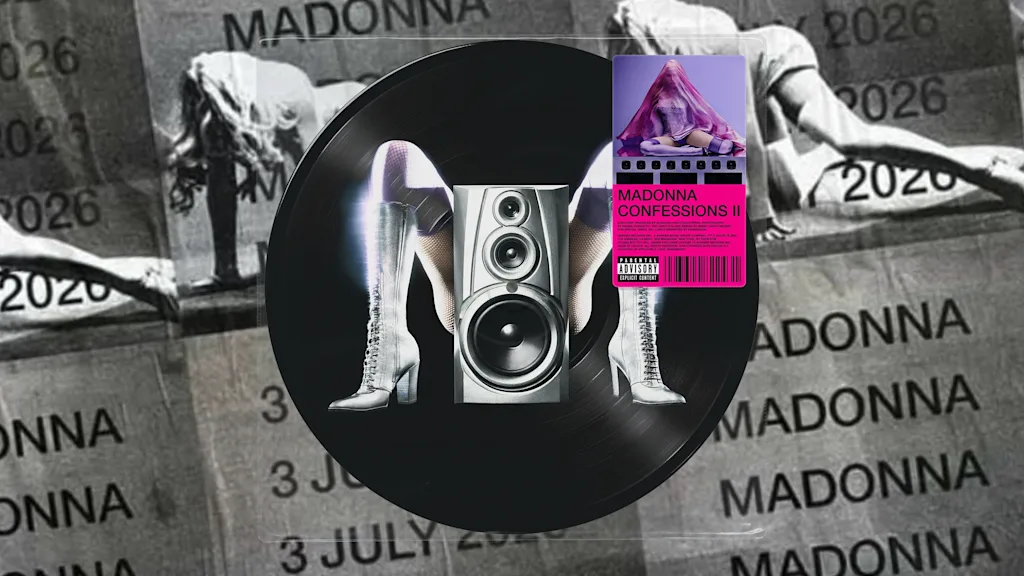
Para a sequência de seu icônico álbum de pop dance de 2005, Madonna voltou a trabalhar com o produtor Stuart Price, responsável por gravar, coproduzir e coescrever o disco original.
O trecho divulgado da primeira faixa reforça essa conexão, mergulhando diretamente no universo pop dance que marcou o álbum original. Já no design gráfico, Madonna optou por uma nova parceria criativa, desta vez com uma abordagem centrada na tipografia.
A agência Special Offer, Inc. já trabalhou com artistas como Haim e Miley Cyrus, mas ganhou destaque global com a direção de arte de "brat", lançado em 2024.
O álbum de Charli XCX, conhecido pela paleta verde neon e pelo uso da fonte Arial Narrow desfocada, levou o prêmio de Melhor Pacote de Gravação no Grammy de 2025.
Depois do lançamento, a estética do texto de "brat" se espalhou rapidamente: virou mural, gerador não oficial de capas, estampou produtos licenciados (e não licenciados) e apareceu até em versões de luxo do álbum.
Se antes Madonna promovia sua música em plataformas como a MTV, hoje é o vídeo curto que dita o ritmo da atenção. A estratégia visual baseada em tipografia adotada pela Special Offer, Inc. funciona perfeitamente em telas de smartphone, onde textos curtos, fortes e visualmente impactantes fazem o usuário parar de rolar o feed.
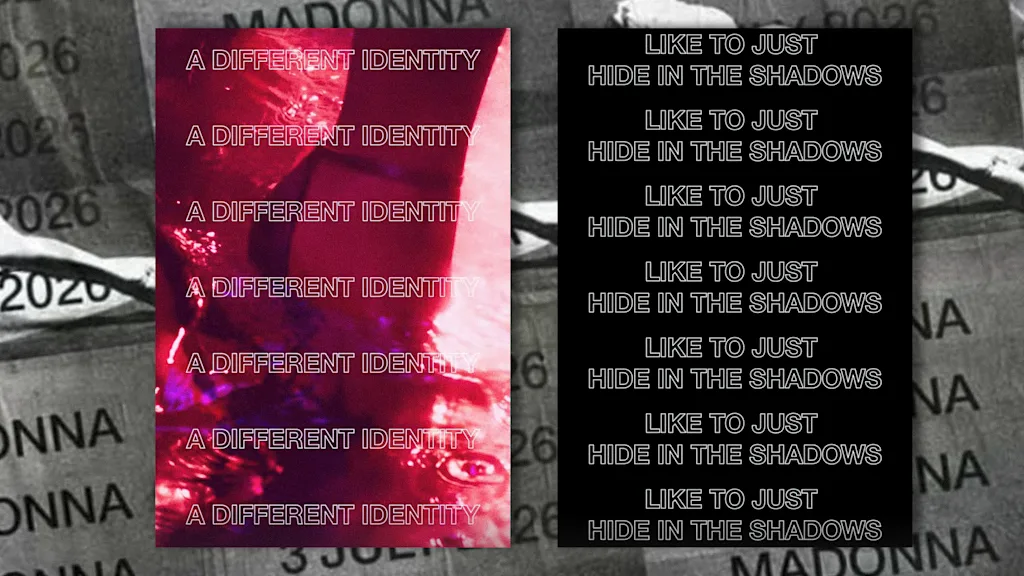
“A tipografia para uma artista como Madonna é algo interessante”, afirma o designer Nolan Strals, que já criou capas para nomes como Titus Andronicus, Beach House e John Legend & The Roots.
“Sempre houve uma conexão com pistas de dança, mas isso parece uma tentativa de se manter relevante para uma nova geração… É uma tipografia que não busca chamar a atenção dos fãs antigos, mas dialogar com quem consome cultura pelo TikTok.”
No álbum original "Confessions on a Dance Floor", a tipografia incluía um logotipo em que a letra “O” virava uma bola de discoteca. O título manuscrito, a lista de faixas e os encartes remetiam à estética das capas da era disco, evocando artistas como Michael Jackson e Grace Jones.
A fotografia ficou por conta de Steven Klein, que retratou Madonna com cabelo vermelho, collant rosa e sapatos brilhantes. A direção de arte e o design gráfico foram assinados por Giovanni Bianco.
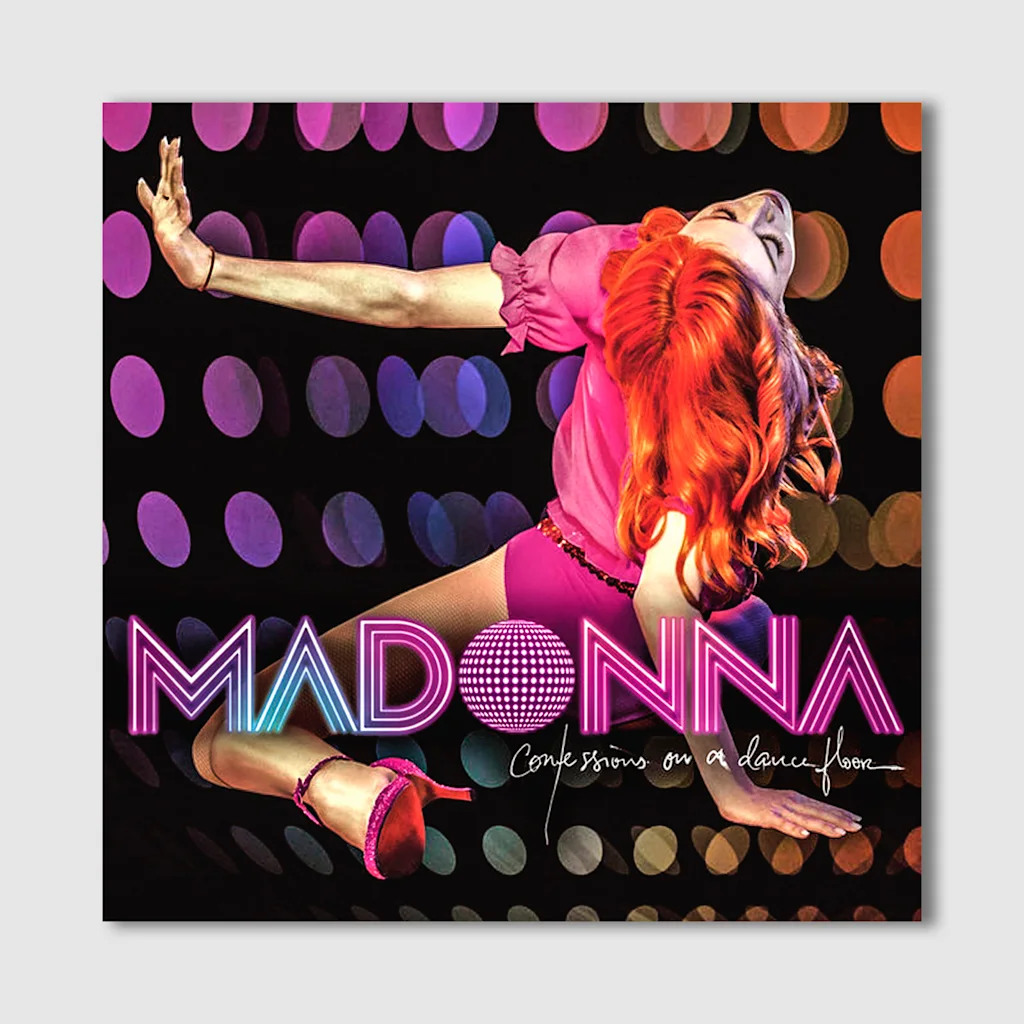
A paleta do álbum – que trouxe hits como “Hung Up” (com sample do ABBA) e “Sorry” – girava em torno de tons de rosa e roxo, com iluminação escura e dramática.
No novo projeto, a combinação de rosa vibrante, vermelho e roxo cria um impacto visual forte, quase irreverente, mas ainda dialoga com as cores do trabalho original.
Já a fotografia de "Confessions II" segue um caminho mais fashionista, com estética editorial de revista: Madonna aparece com tecido sobre a cabeça, vestindo uma blusa floral e meias arrastão. Desta vez, os sapatos abandonam o brilho: são totalmente pretos.
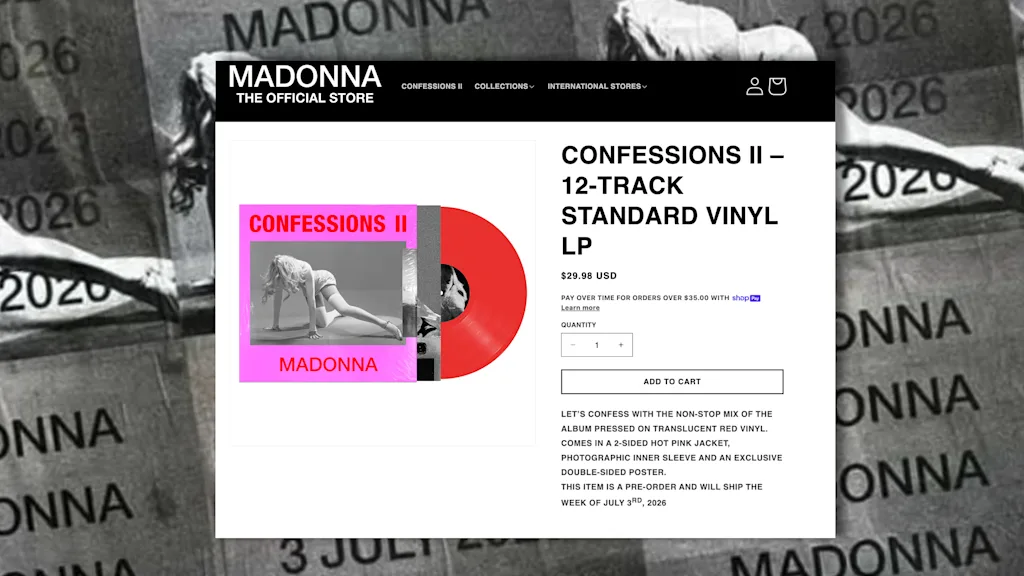
Mais de 20 anos após o lançamento do primeiro álbum, a identidade visual de "Confessions on a Dance Floor" se expandiu para um universo maior, presente em turnês, em um CD/DVD ao vivo e em edições comemorativas.
Agora, na sequência, os designers constroem sobre esse legado. O novo visual é uma evolução – como se o disco tivesse crescido e amadurecido.